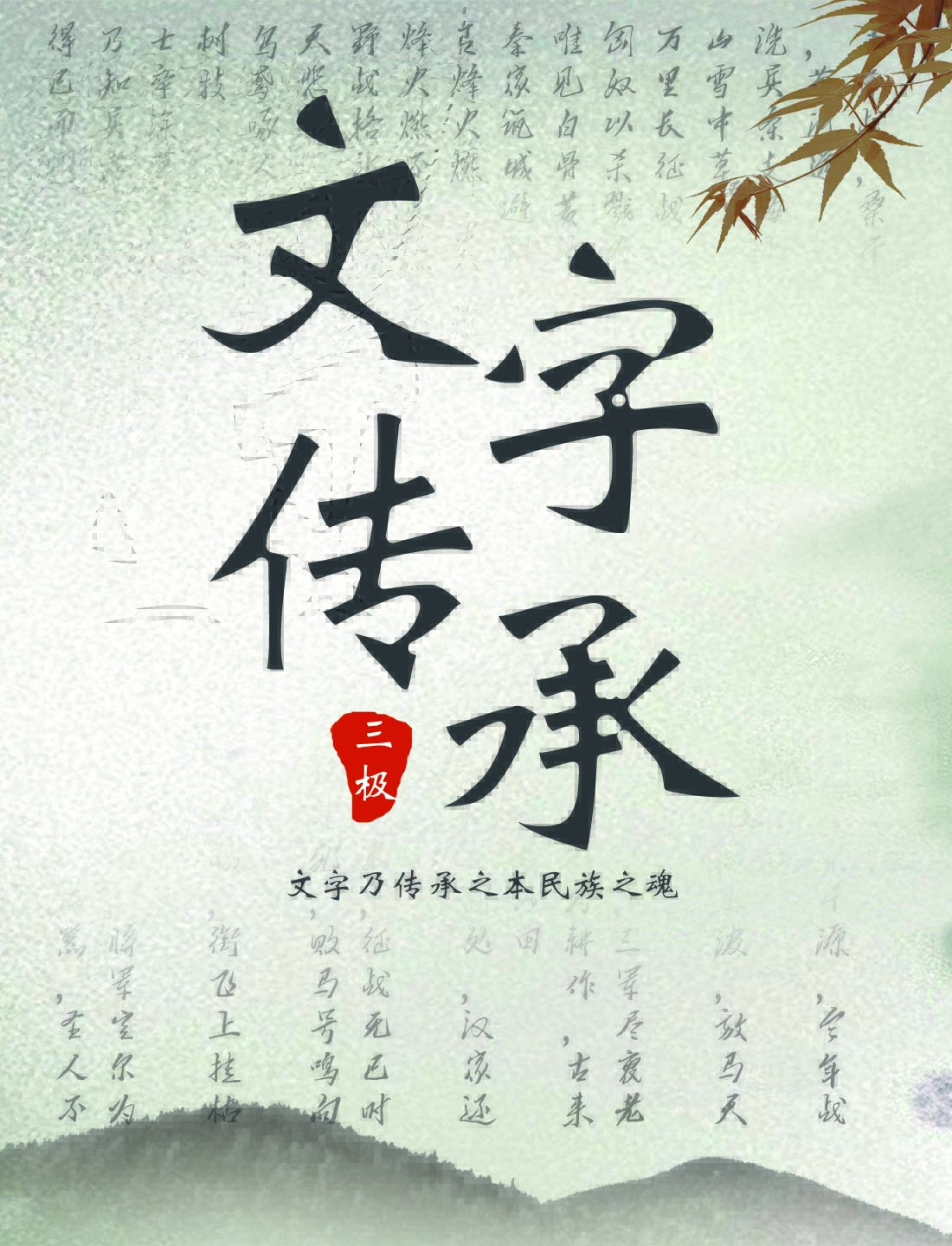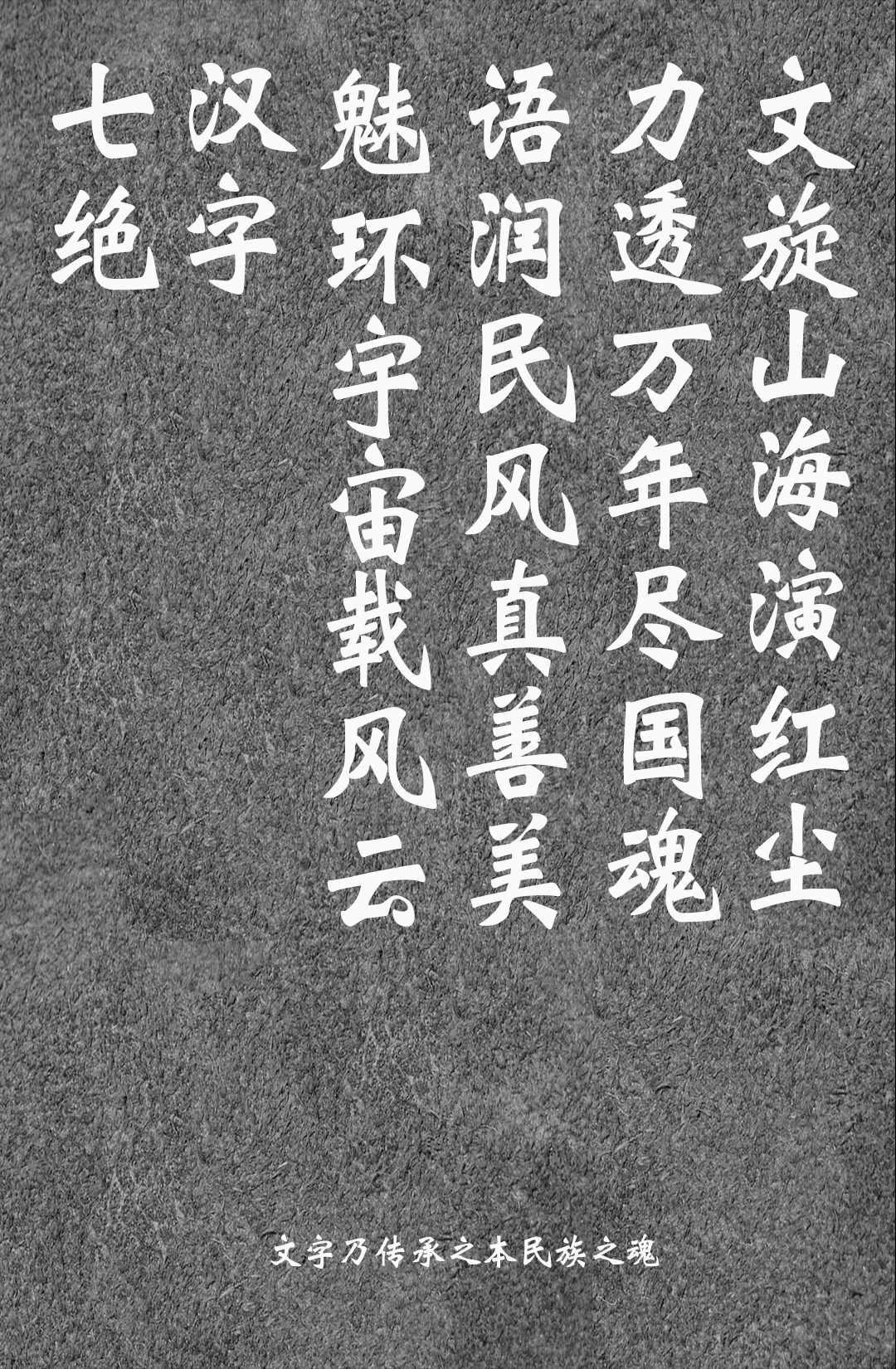
中华大一统的核心纽带---文字
柏杨先生在《中国人史纲》中明确表明:感谢汉字,让中华文明成为了唯一一个史无断绝的古老壮丽文明!
大一统何时形成?统一的看法是秦朝。大一统的一统有货币、度量衡等等,其中影响最深远的一定是书同文,即统一文字。统一文字之后,使全社会各阶层人民有了一个最根本的沟通基础,不管你的语音语法如何改变,都用具有同样意义的同样的文字表达,此之谓同文同种,社会的大融合由此具备基础。
[图上使用的字体: 三极花信简体 三极黄艺明书体]
汉字由于其具象性而具有生命和灵魂,方块字的特点导致其笔画不能够有所删减,由此形成固定程式。而汉文明作为一个精致的农耕文明,具有稳定的发展基础,通过漫长悠远的时间来丰富完善后,最终形成完整的汉字语言系统。
中国在绵延几千年的发展历程中,几次经历几乎灭国灭族的厄运。北魏孝文帝统一整个北方,占领了中华文明的核心地带。但他不能进行有效统治,为何?柔然民族没有文字,即算有,也不完整。如果当时的柔然民族有完整的文字系统,中华文明将不复存在。所以,他只能用汉字系统施政。于是迁都,于是发生了中华民族史上最伟大的一次融合,这是汉字的胜利!其后的蒙元满清都是如此。
[图上使用的字体: 三极隶书简体]
[图上使用的字体: 三极魏碑简体]
放眼世界,和中国一样古老的几个文明为何消失?两个原因。其一,四大文明古国的其他三个其实相连,都以环地中海为文明带。这个文明带的特点是地理环境的开放性以及商贸文明的不稳定性。这两个特性导致文明容易被消灭。其二,汉字之外的其他文字系统都由一个个的字母组成,每个字母单独并无特殊意义,只有组合在一起才代表具体的意义,因此重新单独形成一个文字系统相对容易。我只需要将字母重新组合重新发音就是一个新的文字系统。这样就导致文明被消灭后不能再重新崛起和统一。而中华文明恰好在这两点上具有不可复刻的优势:中华文明是一个高度发达的精致的农耕文明,具有天然的稳定性,又由于东亚地貌的封闭性,导致中华文明几千年来的主要外部入侵势力就是北方游牧民族,游牧文明在生产力低下时代根本无法彻底战胜农耕文明。同样的原因,因为农耕文明的稳定性让人们有充足的时间和空间发展出一个精妙的汉字系统。而一个成熟完整的文字系统没有几百上千年根本不可能完成,所以当一个外来和尚进入中国本土,在只能使用汉字系统的基础上,被同化只是时间问题。同一种文字把松散的一个个社会成员联系在一起,形成民族和民族文化,构成了最为强大的民族凝聚力。因此,中华民族的重新崛起或者说大一统就是必然了。
汉字精妙之处何在?就像近邻日本,用了中国几千个汉字,费心费力改变读音,甚至删减个别笔画,但其内在含义几乎一样!我们甚至可以认为,日本话其实就是我国的一个方言!